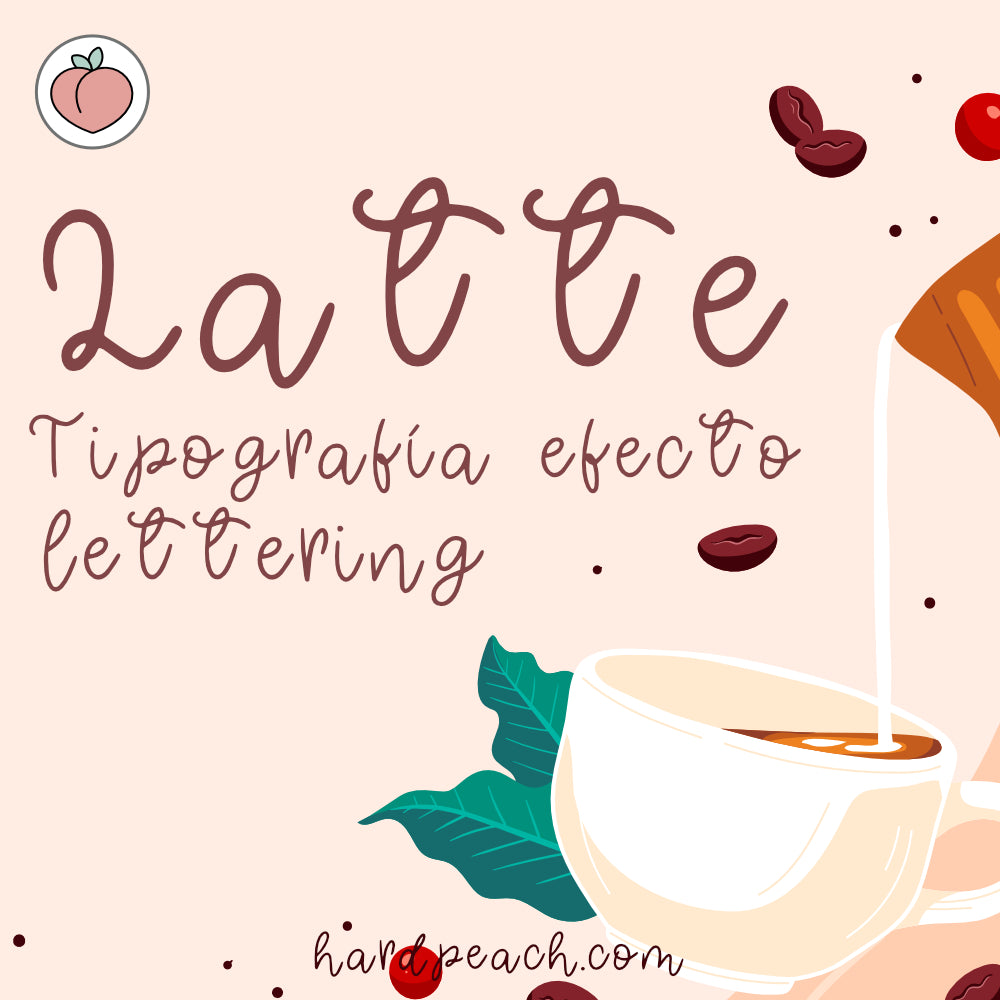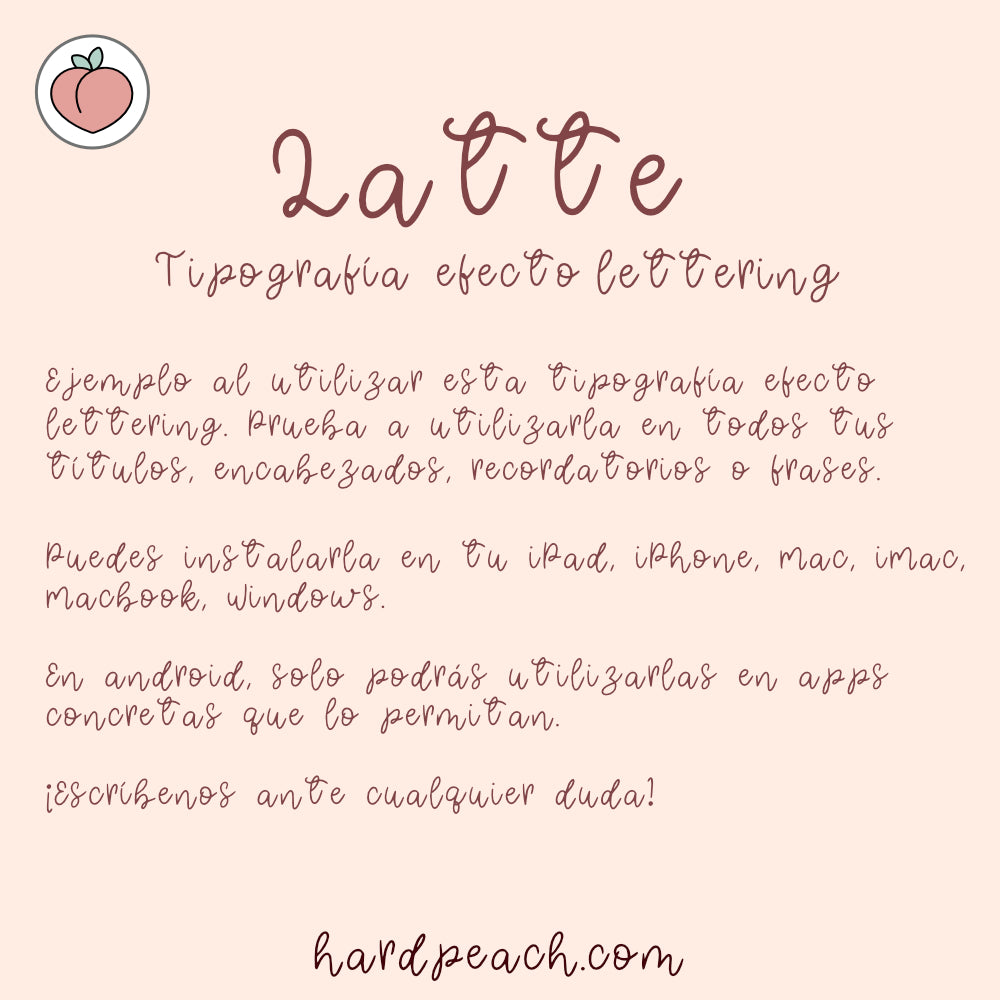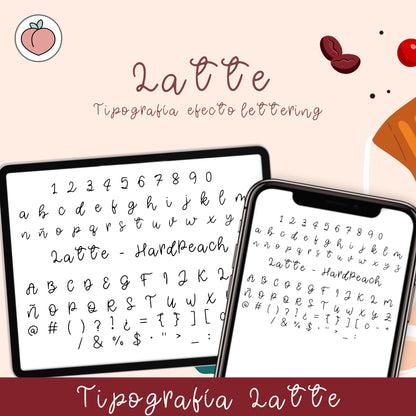
TIPOGRAFÍA LETTERING LATTE: Tipografía digital manuscrita de estilo Lettering. Perfecta para apuntes, agendas, títulos y proyectos creativos
¡Lettering con esta tipografía directamente desde tu teclado! ✨ Tipografía con efecto lettering de trazo fino para todos tus apuntes, títulos y proyectos creativos.
Descubre nuestra tipografía con efecto de lettering de trazo fino, diseñada para escribir de manera elegante y delicada directamente con tu teclado, el teclado virtual de tu dispositivo o incluso transformando tu letra manuscrita con Apple Pencil. Esta tipografía estilo lettering fino es perfecta para apuntes digitales, notas, esquemas, títulos, invitaciones, tarjetas, proyectos de ilustración, bullet journals y cualquier proyecto creativo donde necesites un trazo delicado y profesional.
Con esta tipografía puedes darle un estilo único y artístico a todos tus textos, personalizando colores, tamaños y estilos según tus necesidades. Ideal para estudiantes, creativos, profesionales y cualquier persona que quiera darle un toque elegante y moderno a sus apuntes digitales, planificadores, diarios, tarjetas o ilustraciones.
Ideas de uso:
• Apuntes digitales, resúmenes y esquemas ✏️
• Bullet journals, agendas y diarios creativos 📖
• Títulos elegantes para documentos, presentaciones o proyectos 🎨
• Invitaciones, tarjetas y tarjetas de felicitación 🖌️
• Proyectos de ilustración, diseño gráfico y lettering digital 🌙
Convierte tus notas, agendas, diarios o proyectos creativos en algo profesional, delicado y único con esta tipografía lettering de trazo fino. Expresa tu creatividad, personaliza tus textos y haz que tus apuntes digitales, títulos y diseños brillen con un estilo totalmente moderno, elegante y artístico.
La tipografía Latte incluye todos los caracteres principales, mayúsculas, minúsculas, números, vocales con tildes (español), y acentuaciones abiertas (à) y signos. Además, incluye la acentuaciones y las letras ñ y ç.
Ideal para títulos
Es una tipografía súper bonita para aplicarla en títulos. Es mi favorita, me encanta!
lettering con el teclado
similar a lettering, es muy interesante esta fuente
muy bonita